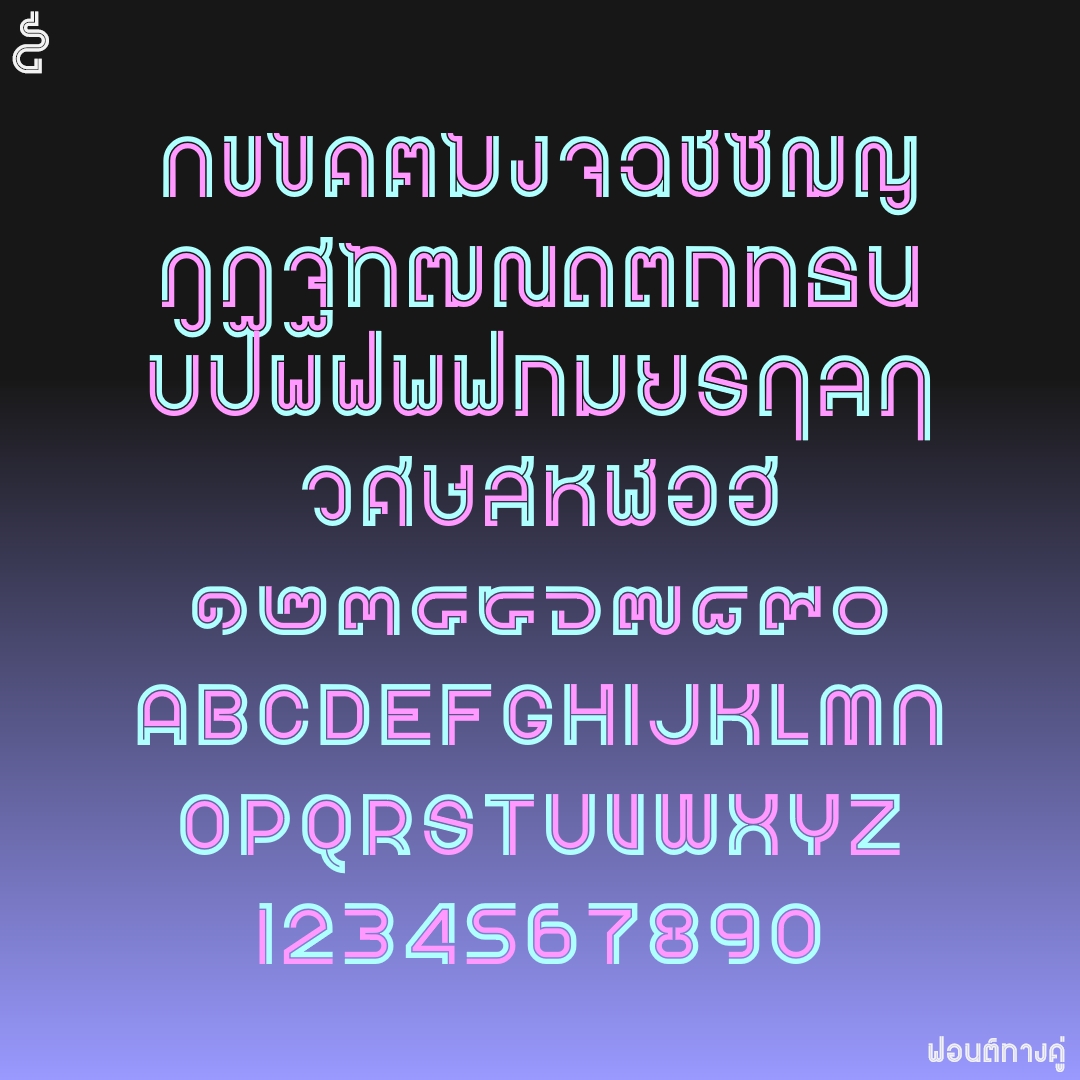
ฟอนต์ ทางคู่
ฟอนต์ทางคู่ อักษรไทยไม่มีหัวแต่มีหัว ตัวเดียวแต่สองฟอนต์ ทำสองสีได้ เวลาใช้ยุ่งหน่อย ต้องซ้อนตัวปรกติ กับตัว bold
ชื่อฟอนต์ : ทางคู่
ฟอนต์ทางคู่ อักษรไทยไม่มีหัวแต่มีหัว ตัวเดียวแต่สองฟอนต์ ทำสองสีได้ เวลาใช้ยุ่งหน่อย ต้องซ้อนตัวปรกติ กับตัว bold